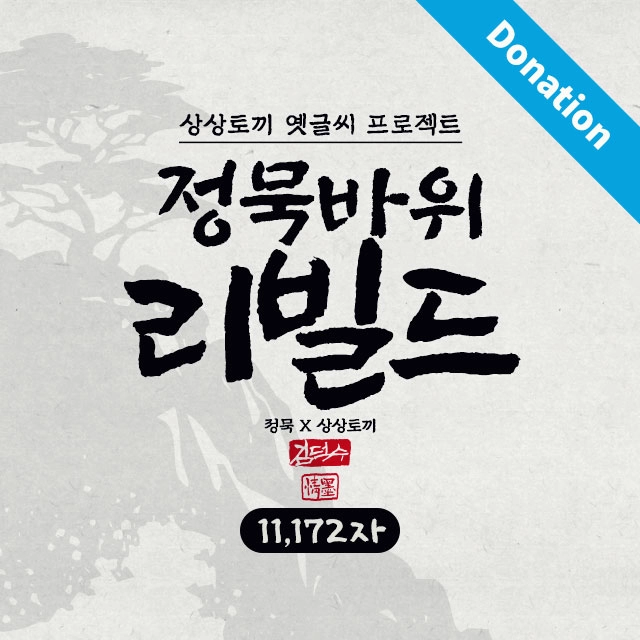
정묵 바위 리빌드
정묵 작가가 기존 정묵 바위의 획을 직접 재조합하고, 형태가 만족스럽지 않았던 일부 획은 추가로 보완을 하여 새롭게 만든 폰트, 정묵 바위 리빌드 ♥ 기부형 폰트
한글 11,172자 / 영문 52자 / 약물 50자
정묵 바위 리빌드 Regular 1종